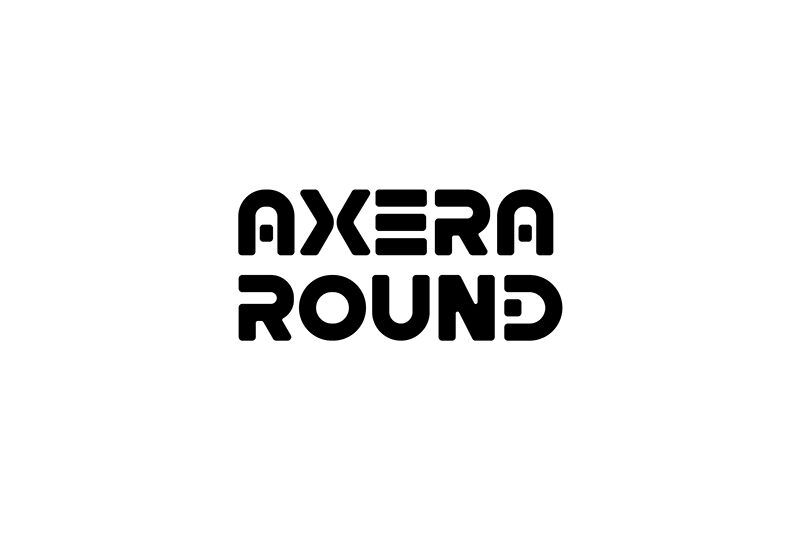
Axera Round von YP7 Studio ist eine kostenlose, futuristische Display-Schrift mit einer weichen, organischen Anmutung. Die Buchstaben wirken wie aus massiven, abgerundeten Blöcken gebaut; eine Kombination aus breiten Kurven, prägnanten Verbindungen und kompakten Öffnungen, die dem Design eher einen freundlichen Sci-Fi-Look als eine kühle Techno-Ästhetik verleiht.
Damit eignet sie sich perfekt für Gaming-Grafiken, Cover-Designs, Poster-Titel, App-Branding und Verpackungen, die eine retro-futuristische Stimmung vermitteln sollen. Als kostenlose Schrift funktioniert sie besonders gut in kurzen Überschriften, Titelkarten und logoartigen Schriftzügen, wo diese massiven, abgerundeten Formen die Botschaft grafisch und einprägsam in Szene setzen.
YP7 Studio
Axera Round